La imprenta se extendió velozmente. William Caxton la llevó a Inglaterra en 1476. Este fascinante personaje, natural de Ken (1422, fecha probable de nacimiento) no era un gran impresor desde el punto de vista técnico. Había aprendido el arte en el continente, posiblemente en Colonia; en 1475 imprimía en Brujas el primer libro en inglés, su propia traducción de Receuil des Histoires de Troies, e instaló su imprenta en Westminster. Hacia 1476 la imprenta había llegado ya a Italia, Suiza, Francia, los Países Bajos, Bélgica, Hungría, Polonia y España. Todos los tipos que Caxton usaba eran variedades de la gótica negra, sus obras primerizas están compuestas con familias flamencas porque fue en los Países Bajos donde adquirió sus primeros útiles. Su capataz y sucesor, el alsaciano Wynkyn de Worde, utilizó la letra redonda por primera vez en 1510, aunque Richard Pynson, que había compuesto un libro con ella once años atrás, es el pionero de su empleo en Inglaterra, donde fue desplazando poco a poco a la gótica negra para usos corrientes. Dice Johnson: «El que, en última instancia, los impresores ingleses adoptaran la letra redonda como tipo estándar, parece haber sido casi accidental.» Lo achaca al hecho de que los impresores ingleses del siglo XVI, muy constreñidos por la censura religiosa y política, admiraban y seguían a los impresores franceses y éstos se habían decantado por la redonda. Así pues, la primera edición de las obras de Shakespeare se compuso e imprimió en caracteres redondos.
De Plantin a Bodoni:
A principios del siglo XVI, los libros impresos empezaban a convertirse en objetos verdaderamente autónomos y no meras copias de manuscritos, pero ello no sin oposición. Los copistas, que veían en el avance de la imprenta una amenaza mortal para su medio de vida, cerraron filas frente a ella y hay testimonios de que más de un bibliófilo adinerado declaró que jamás admitiría libros impresos en su biblioteca. Al principio gradualmente y luego con rapidez, el advenimiento de la imprenta acabó con el oficio de copista; sólo entonces la impresión tipográfica quedó en libertad para establecer convenciones y características propias. La portada, que casi nunca había existido en los manuscritos, devino normal; generalmente se imprimía en ella el nombre del impresor (que era también el editor) y su marca. Se inventó la cursiva en Italia (razón por la cual también se la llama itálica) partiendo de una veloz caligrafía en la cancillería se reservaba para determinadas clases de documentos y que por ello se conocía como «escritura cancilleresca». La bastardilla (otro nombre de la cursiva) se convirtió pronto en una alternativa tipográfica para los caracteres redondos, ya que tenía la ventaja de ser al mismo tiempo compacta y elegante; continuó siendo una familia tipográfica por derecho propio durante dos siglos y sólo muy gradualmente dio su uso en transformarse hasta lo que es hoy, un mero auxiliar de la redonda. Desde principios del siglo XVI se cayó en la cuenta —especialmente en Italia y Francia— que ya no hacía falta decorar a mano los libros impresos: en este momento comienza a existir el arte del diseño del libro impreso.
Los libros franceses del XVII, decorados con ornamentos tipográficos e ilustraciones y márgenes xilografiados, establecieron unos estándares para el diseño artístico del libro que tal vez continúen insuperados. Este fue el período de Estienne, Simón de Colines, Geofroy Tory, Claud Garamond, Jean de Tournes, Robert Granjon y otros muchos grandes nombres de la historia de la impresión. Johannes Froben hizo de Basilea (Suiza) un centro impresor famoso: era amigo y editor de Erasmo. Holbein le hizo un retrato memorable y diseñó márgenes xilografiados para ediciones suyas.
De entre los impresores-editores del siglo XVI el más célebre quizá sea Christopher Plantin (h. 1510-1580), también francés; en 1555 se instaló en Amberes, donde creó un establecimiento impresor que habría de seguir funcionando durante casi tres, siglos. Al morir Plantin (1580) se hizo cargo del negocio su yerno Jan Moretus, para cuyas ediciones Rubens creaba portadas en plancha de cobre. Una extraordinaria combinación de suerte y cuidados ha hecho que la casa ocupada por la Imprenta Plantin exista aún y, con ella, buena parte de los útiles originales. Bautizada actualmente como el Museo Plantin-Moretus de Amberes, es un fascinante lugar de peregrinación para los tipógrafos.
El siglo XVIII fue testigo del florecimiento de la tipografía en Gran Bretaña. William Caslon (1692-1766) era inicialmente armero, pero cambió el grabado de las culatas por la talla de punzones para tipografiar encuademaciones y de aquí pasó a tallar los famosos caracteres que todavía hoy se Usan. Sus modelos fueron los mejores tipos holandeses del siglo XVII. Uno de los admiradores de Caslon era John Baskerville (1706-775), que tras ser maestro calígrafo y grabador, amasó una fortuna en Birmingham con el comercio de los charolados metálicos, pasándose entonces a la impresión. Diseñó y talló una familia nueva (que, en distintas versiones, es aún hoy uno de los más populares tipos para libros ingleses), construyó una prensa nueva, se preparaba sus propias tintas, especificaba cómo habían de fabricarle el papel y, tras la impresión, apretaba los pliegos entre planchas de cobre calientes para realzar el efecto. Su primer libro, Virgil, impreso en 1757 «cobraba impulso para anonadar a todos los bibliotecarios de Europa». Se convirtió en el primer impresor inglés desde Caxton a cuyos libros se alude más por su nombre que por el de los autores, Su estilo, clásico y severo, no se apoya en ornamentos o ilustraciones de ninguna clase, como la mayor parte de los libros de su época. Como muestra final de su toma de partido por el racionalismo contra la superstición, dejó dispuesto en su testamento que se le enterrara de pie en la tierra sin consagrar de su jardín de Easy Hill, en las afueras de Birmingham
Mientras Caslon era un comerciante cuya ocupación consistía en hacer tipos y venderlos, Baskerville era un hombre de negocios que llegó a la tipografía por placer y que la consideraba un arte. Estas discrepancias en el modo de entender la tipografía aparecerán una vez tras otra a partir de ahora hasta converger, a principios de siglo, en la persona de un profesional nuevo del negocio impresor, el tipógrafo, que además de ganarse la vida con su oficio pretende, al tiempo, ser artista.
Aunque tal vez, el tipógrafo actual, que aplica su capacidad y su formación artística al desempeño de una actividad comercial, ha existido siempre en las artes gráficas, o al menos desde el siglo XVII. Un ejemplo notable fue el contemporáneo francés de Baskerville, Fierre Simón Fournier el Joven (1712-1768). Este hombre, nacido en una familia de impresores, aprendió dibujo en la Academia de St Lúe de París antes de ponerse a trabajar a las órdenes de su hermano en una fundición. En 1742 publicó su célebre muestrario Modele des "Caracteres de I'imprimerie" y un "Caracteres de l'imprimerie", más pequeño, con los que estableció su reputación. En 1764-1766 publicó su no menos famoso Manuel Typographique. Las romanas de Fournier eran ligeramente más estrechas que la mayoría de las familias anteriores; su cursiva, reputada como «la más legible de todas las cursivas», «llevaba la noción de la concordancia con la redonda más allá que la de cualquier diseñador previo» y sus viñetas «certifican la suprema maestría de su autor en el ornamento tipográfico». Además de todo ello, Fournier fue el primero en comprender la necesidad de racionalizar los cuerpos medidas de los caracteres: en 1737 hizo público su sistema del punto tipográfico, desarrollado a tal fin. Es uno de los escasísimos diseñadores en la historia de las artes gráficas capacitado simultáneamente, para tallar punzones,fundir matricería e imprimir.
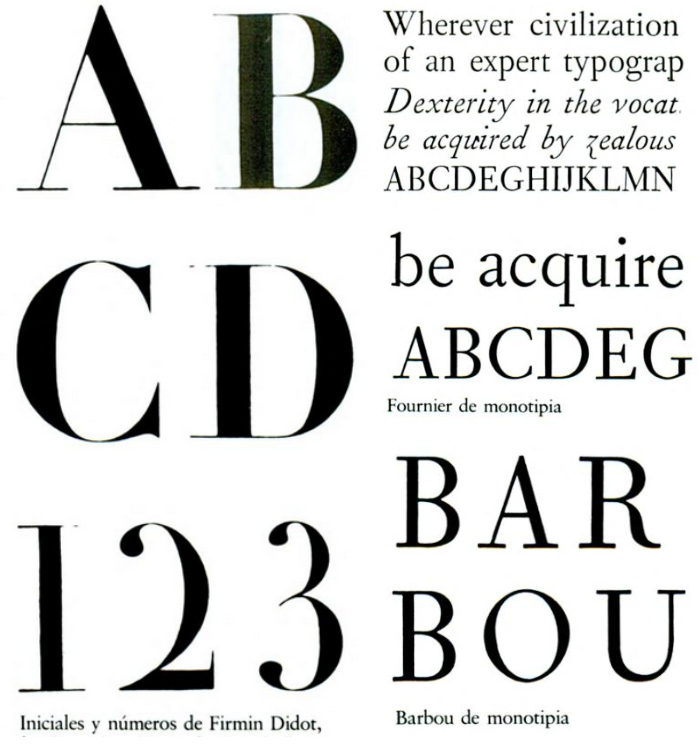
En 1925, la Monotype Corporation adaptó y lanzó al mercado la redonda y la cursiva de Fournier, que se situaron durante los años treinta entre los tipos para libro más populares. Los caracteres y ornamentos se describían e ilustraban brillantemente en un número doble de The Monotype Recorder diseñado, escrito y confeccionado por Paul Beaujon (Beatrice Warde) en 1926. Se reveló posteriormente que antes de que se tomara la decisión de lanzar al mercado las Fournier para composición monotípica, se tallaron dos diseños distintos identificados como serie 185 y 178 respectivamente y «que a causa de una confusión (propiciada porque el asesor competente se hallaba en el extranjero) fue aprobado la serie 185». Se usó para el Shakespeare en siete volúmenes de la Nonesuch Press, publicación que Francis Meynell consideraba la obra maestra de su editorial, de la que Morison dijo que era «un no más pequeño monumento a Fournier el Joven, aunque la altura de las mayúsculas sea particularmente reducida». La versión mejor (serie 178), a la que se bautizó «Barbou», estuvo disponible solamente en un cuerpo durante largo iempo: se usó en los tres últimos volúmenes de The Fleuron, el boletín tipográfico de Stanley Morison. Desde 1967, sin embargo, están disponible solamente en un cuerpo (pueden verse y compararse con la de la serie 185) en la excelente obra de Alien Hutt Fóumier, The compleat typographer(Londres, 1972).
Los tipos romanos de Caslon y sus predecesores, que solemos considerar derivados de la «romana antigua», se basaban en los trazos realizados con pluma de punto cuadrado: si se desplaza lateralmente la línea es fina, si se mueve hacia abajo gruesa. El modo más fácil de sujetar una pluma para la mano de quien escribe es procurar mantenerla en ángulo de aproximadamente 45° con la línea de avance. El efecto sobre letras redondas como la «e» y la «o» se conoce en tipografía como «modulación oblicua».
En el siglo XVIII, denominado a veces la Era de la Razón, los caracteres tipográficos dejaron de ser meras copias de unas escrituras u otras y se convirtieron en formas autónomas sujetas a desarrollo tanto artístico como intelectual. Baskerville diseñó sus tipos alejándose levemente de la modulación oblicua, pero el siguiente paso decisivo lo dio un francés llamado Firmin Didot con la creación de lo que se conoce como romana moderna, donde la modulación es vertical (perpendicular a la linea) y los remates o terminales son filiformes. Aunque era ésta una solución intelectual y teórica lógica que nunca había atraído demasiado a los tipógrafos anglosajones, los tipos «modernos» se convirtieron rápidamente en los más usados para casi todo el material de lectura francés y así han continuado hasta hoy.
Ni los tipos ni el estilo de tipografía bodonianos podrían calificarse nunca de «animados» pero, antes incluso de la muerte de Bodoní (1813), fundidores ingleses que trabajaban sobre la contraposición grueso/fino y la modulación vertical desarrollaron la Fat Face con propósito de utilizarla en publicidad; se trata de unos caracteres que, especialmente en la variante cursiva, resultan positivamente joviales. El padre de la Fat Face parece haber sido Robert Thorne (1794-1820), el distinguido diseñador y fundidor tipográfico. Aunque pudiera no haberse inspirado en Bodoni, la conexión es obvia y así lo reconoció la Monotype Corporation cuando punzonaron la Bodoni Ultra, una Fat Face que (tal vez por deferencia a su homónima) ha perdido los rizos y las manchas que muestran los ejemplos decimonónicos.